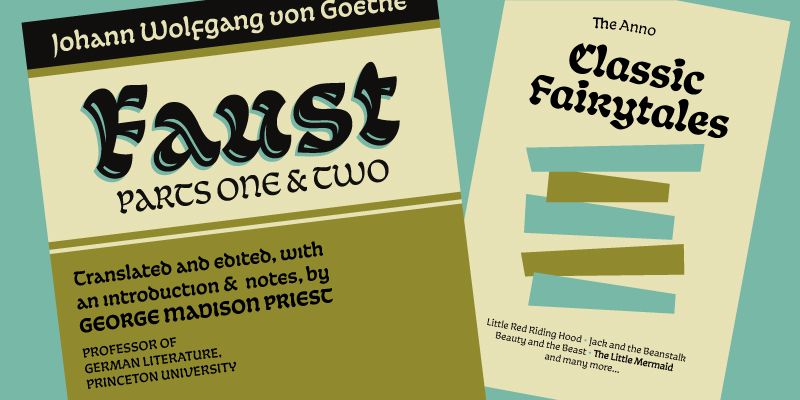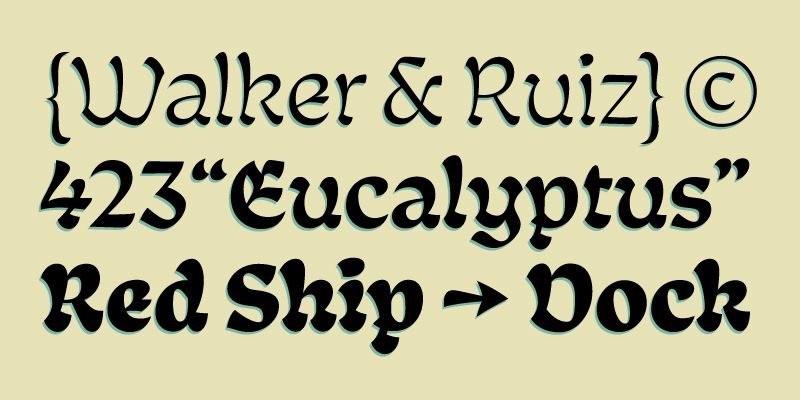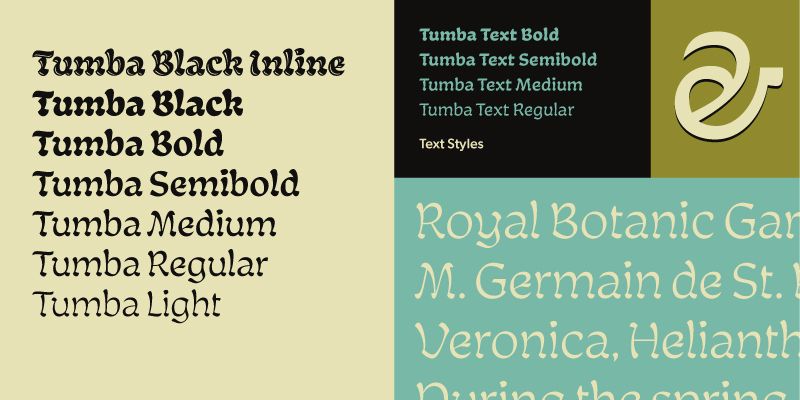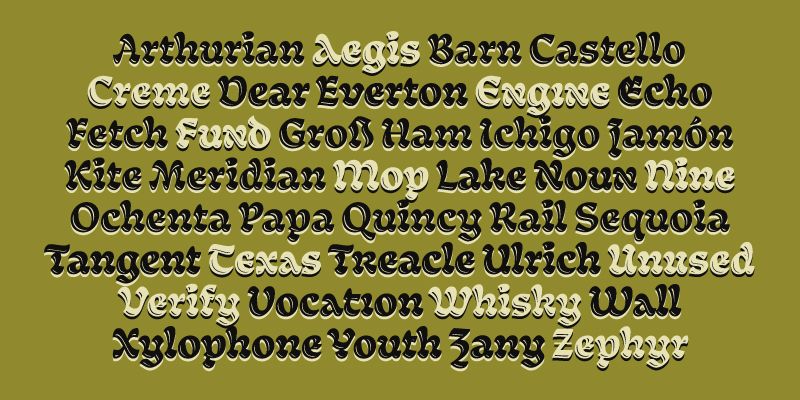
Tumba trae ispirazione da due diversi generi storici, l’onciale e il gotico, e riesce a interpretare le antiche forme attraverso una lente moderna con un tratto e un dotto unici.